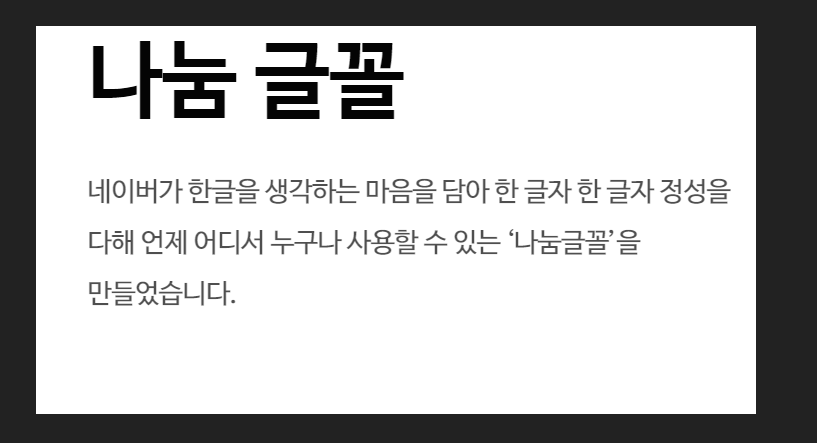
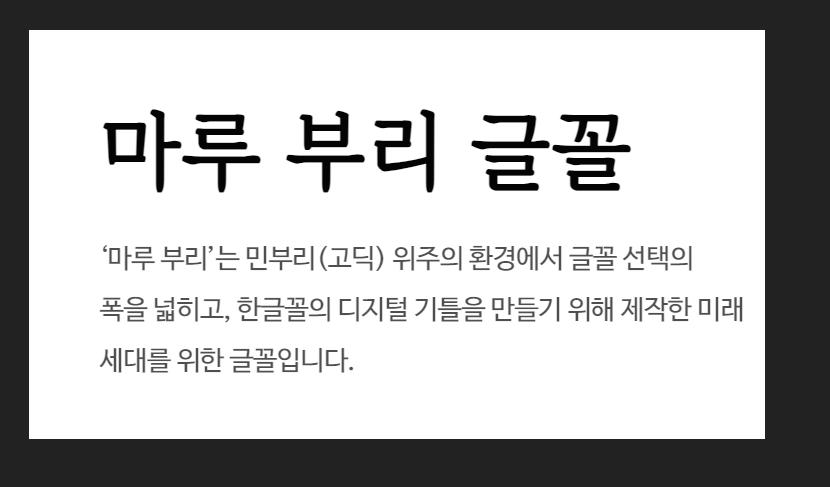
- 다양한 용도의 폰트를 활용하여 더욱 창의적인 디자인을 시도해 보세요.
- 영어 폰트와 비교했을 때, 한글 폰트는 수가 적으며 무료인 경우가 드뭅니다.
- 디자인에서 중요한 요소는 이미지뿐만 아니라 글씨체와 폰트도 포함됩니다.
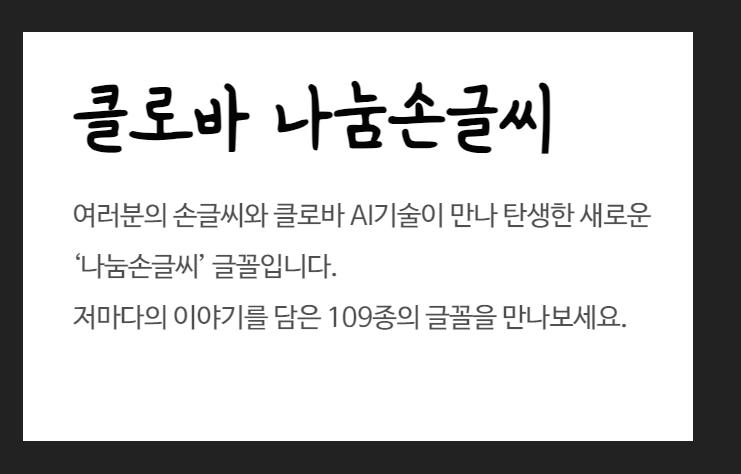
- 글꼴을 선택한 후 글을 입력해 보고, 다른 글꼴들과 비교하는 것이 가능합니다.
- 첫 닿자, 홑자, 받침자로 조합 가능한 모든 한글 표현이 가능하게 제작된 폰트를 사용하세요.
- 깨짐 현상이 없으며, 인쇄, 웹, 모바일에서 모두 잘 보이는 글자를 사용하세요.
- 디자인일을 하는 사람들이 주로 사용하는 폰트를 모아놓았습니다.
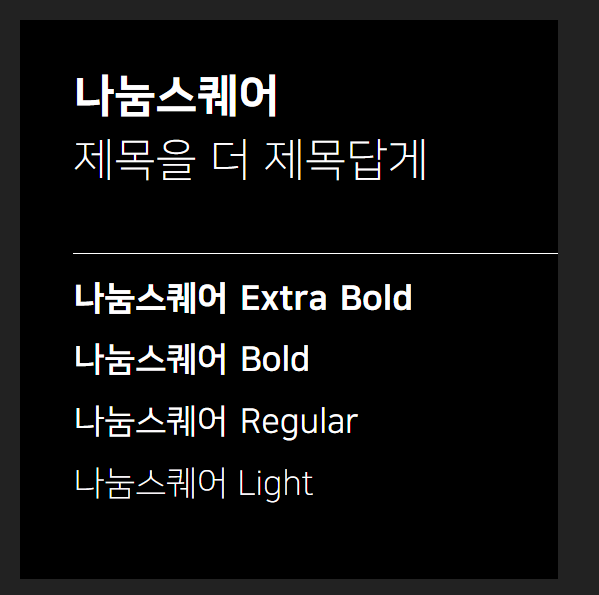
폰트는 텍스트의 주제나 목적에 따라 다양하게 변화할 수 있습니다. 예를 들어, 공식적인 문서나 비즈니스 관련 텍스트에는 심플하고 정돈된 폰트가 적합하고, 친근하고 재미있는 텍스트에는 독특하고 개성 있는 폰트가 어울릴 수 있습니다. 무료 한글 폰트를 다운로드 받아보세요!
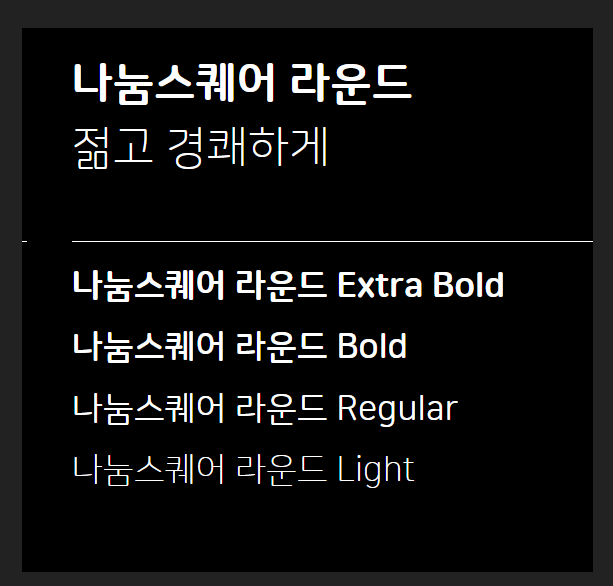
- 가독성 향상: 다양한 폰트를 활용하여 텍스트에 색다른 분위기를 부여하세요.
- 적합한 폰트: 텍스트의 목적이나 성격에 맞는 폰트를 선택하세요.
텍스트의 목적에 맞는 적절한 폰트를 선택하면 디자인의 완성도가 한층 더 높아질 것입니다. 지금 바로 새로운 폰트를 다운로드하여 여러분의 디자인을 한층 더 매력적으로 만들어 보세요! 폰트의 중요성 및 활용폰트는 텍스트의 스타일과 분위기를 만들어주며, 텍스트의 가독성을 좌우합니다.
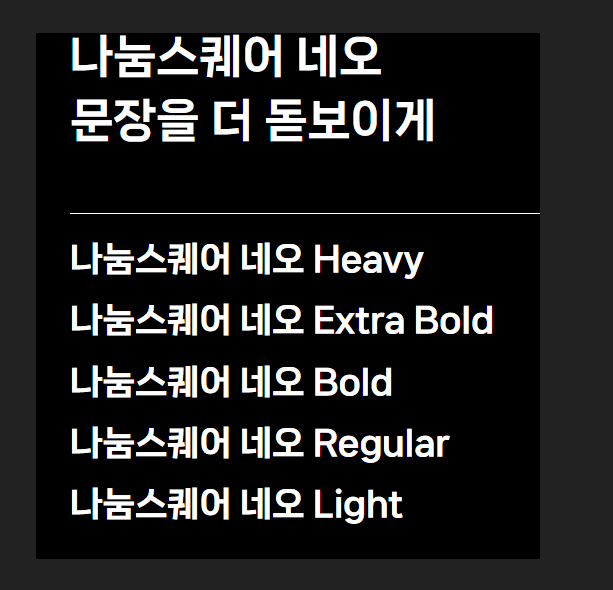
텍스트를 효과적으로 전달하기 위해 적절한 폰트를 선택하는 것이 중요합니다.
- 스타일 및 분위기: 다양한 폰트의 크기, 색상, 간격 등은 텍스트가 눈에 잘 들어오고 읽기 쉬운지에 큰 영향을 미칩니다.
- 가독성과 가시성: 굵고 큰 폰트는 강조할 때 유용하며, 세련된 폰트는 전문적이고 신뢰를 주는 인상을 줍니다.
- 의미와 감정 전달: 다양한 폰트는 텍스트의 감정을 효과적으로 전달하는 데 중요한 역할을 합니다.
여러분이 블로그나 유튜브 썸네일을 제작할 때, 또는 문서나 웹사이트 디자인 시 반드시 고려해야 할 요소가 바로 폰트입니다. 적절한 폰트 선택은 텍스트의 가치를 높일 수 있습니다.
236종의 무료 폰트를 저작권 걱정 없이 다운로드하여 사용할 수 있는 방법을 통해 더 많은 정보를 제공합니다.
폰트 소개 및 활용법 지원 사업을 통해 일상생활에 필요한 다양한 정보를 공유합니다.
글꼴 다운로드를 위한 안내는 다음과 같습니다: 하단에는 다음과 같은 글꼴들이 나열되어 있습니다.
주로 나눔 글꼴, 마무 부리 글꼴, 크로버 나눔 손글씨로 구성되어 있습니다. 오른쪽에 표시된 다운로드 버튼을 클릭하면 다양한 서체를 한 번에 다운로드할 수 있습니다.
1. 글꼴 다운로드 방법: - 메인 화면으로 들어가면 하단에 글꼴 모음이라는 아이콘을 확인할 수 있습니다.
- 해당 아이콘을 더블 클릭하여 들어가 주세요.
- 새로운 화면이 나타납니다. 이 화면에서는 다양한 글꼴의 정보를 확인할 수 있습니다.
내용을 무시하시고 스크롤을 아래로 내려주시면 됩니다.
2. 셋방고딕체 사용 방법: - 세방고딕체는 디자인 측면에서 매우 아름다운 폰트로, 문서의 첫 페이지에 제목용으로 사용하기 적합합니다. - 시옷이 예쁜 폰트로 알려져 있으며, 다양한 디자인 작업 시에도 활용하기 좋습니다. - 만약 이미지로 설명이 복잡하다면, 글 아래에 제공된 영상에서 다운로드 방법을 자세히 확인하실 수 있습니다. --- 세방고딕체 설치 및 활용법 요약:
- 메인 화면으로 이동 후 글꼴 모음 아이콘을 더블 클릭하여 들어갑니다.
- 화면 하단으로 스크롤하여 다양한 글꼴을 확인합니다.
- 필요한 글꼴의 다운로드 버튼을 클릭하여 서체를 다운로드합니다.
이와 같이 폰트를 활용하여 문서의 타이틀을 보다 돋보이게 만들고, 다양한 창의적인 프로젝트에서 활용해 보세요. 예쁜 폰트의 효과로 문서의 전체적인 완성도가 크게 향상될 것입니다.
폰트 다운로드 및 활용법파워포인트 폰트 추가 방법에 대해 알아보겠습니다. 셋방고딕 Bold 폰트를 사용하여 제목을 만들었습니다.
글꼴 스타일에서 원하는 폰트를 선택하여 적용할 수 있습니다. 이렇게 하면 슬라이드에 글자를 입력하는 것이 더 쉽습니다. 폰트 다운로드와 설치 방법을 포함하여 문서에 적용하는 방법을 알아보겠습니다.
- 폰트 다운로드: 인터넷을 통해 원하는 폰트를 검색하여 다운로드합니다.
- 설치 방법: 제어판에서 글꼴 폴더를 열고 다운로드한 폰트를 추가합니다.
- 적용 방법: 문서 프로그램에서 새로 추가된 폰트를 선택하여 글자를 입력합니다.
셋방고딕체 설치 확인: 글꼴 폴더에서 다른 두께로 표시된 파일이 보인다면 다양한 폰트를 사용할 수 있습니다.
| 특징 | 설명 | |
| 크기 | 너무 작거나 연하면 읽기 어려울 수 있습니다. | |
| 색상 | 배경과 조화를 이루어야 합니다. | |
| 글꼴 종류 | 특징 | |
| 나눔 글꼴 | 다양한 서체로 구성 | |
| 마무 부리 글꼴 | 독창적인 디자인 | |
| 클로바 나눔 손글씨 | 손글씨 느낌 | |
| 단계 | 설명 | |
| 1 | 인터넷에서 폰트 다운로드 | |
| 2 | 글꼴 폴더에 설치 | |
| 3 | 문서 프로그램에 적용 |